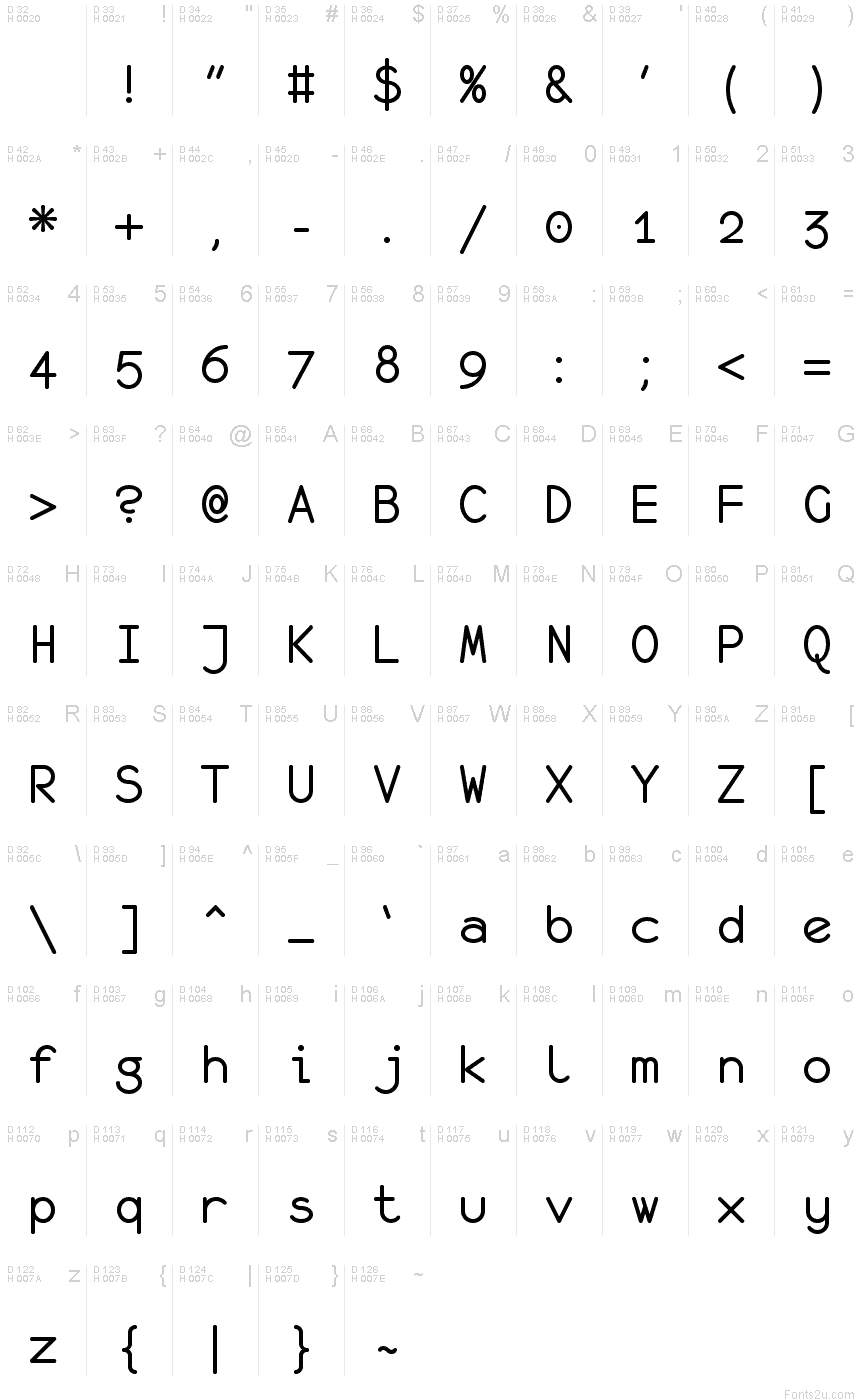
monofur
Font Monofur autorstwa Tobiasa B Kohlera to bezpłatny krój bezszeryfowy o zaokrąglonej, monolinearnej strukturze i wyraźnie prostym, geometrycznym rytmie. Jego małe litery wyróżniają się miękkimi łukami i otwartymi światłami, podczas gdy górne partie wyższych znaków nadają mu precyzyjny, nieco techniczny sznyt, nie sprawiając przy tym wrażenia sztywności.
Monofur świetnie sprawdza się w etykietach technologicznych, makietach aplikacji, tytułach plakatów, blogach programistycznych i minimalistycznym brandingu, ponieważ równomierne kreski i łagodne narożniki zapewniają spójność zarówno w krótkich, jak i długich wyrazach. Ten darmowy font pasuje również do akcentów w interfejsach, składu zina i małych logo, gdzie minimalistyczny krój bezszeryfowy potrzebuje wyraźnego, nieco nietypowego charakteru.